Вставка буквицы — Служба поддержки Майкрософт
Буквицы (буквицы) — это большая буква, используемая в качестве декоративных элементов в начале абзаца или раздела. Размер cap обычно составляет две или более строк.
На рисунке ниже показаны варианты размещения буквицы.
Curly Font Generator (копирование и вставка)
𝓒𝓾𝓻𝓵𝔂 𝓕𝓸𝓷𝓽 𝓖𝓮𝓷𝓮𝓻𝓪𝓽𝓸𝓻 ✅ является одним из самых 𝒮𝓊𝓅ℯ𝓇𝒾ℴ𝓇 онлайн бесплатных инструментов для
создание различных комбинаций букв, 😉 смайликов, символов ( ͡❛͜ʖ ͡❛) и ➰ причудливых прикольных текстов, используемых тысячами людей в
Мир.
Вы также можете создать ⓕⓐⓝⓒⓨ привлекательный текст, который будет работать в 𝓅𝑒𝓇𝓈𝑜𝓃𝒶𝓁 𝓂𝑒𝓈𝓈𝒶𝑔𝑒𝓈, веб-сайтах 🌐, блогах и
подписи.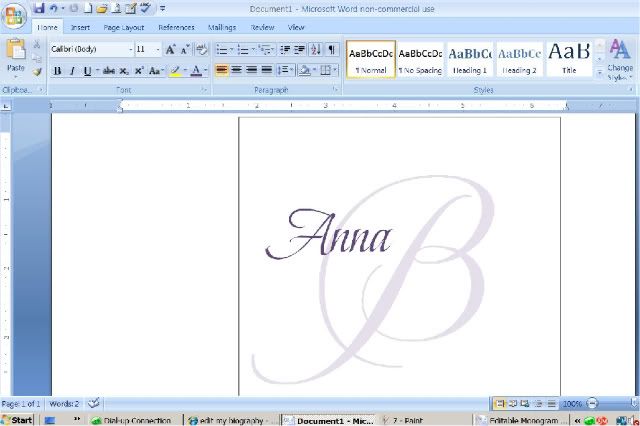
О генераторе фигурных шрифтов
Curly Font Generator Преобразует обычный текст в фигурный текст Unicode, что делает ваш текст более привлекательным.
стильный и привлекательный.
Вы можете скопировать и вставить этот изогнутый текст в свои Facebook, Twitter, Instagram и другие социальные сети.
посты и статусы в СМИ.
Вы можете использовать CurlyText Generator для своего веб-сайта, блога, заголовка, логотипа и сериала. Вы можете использовать его
Поддержка стильных шрифтов для разных устройств
Причудливые шрифты используют символы и смайлики, которые в настоящее время поддерживаются большинством устройств, но все же вы можете скопировать причудливый шрифт и проверить, совместим ли причудливый шрифт с вашим устройством или нет.